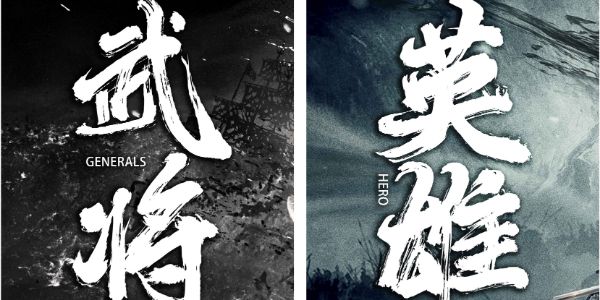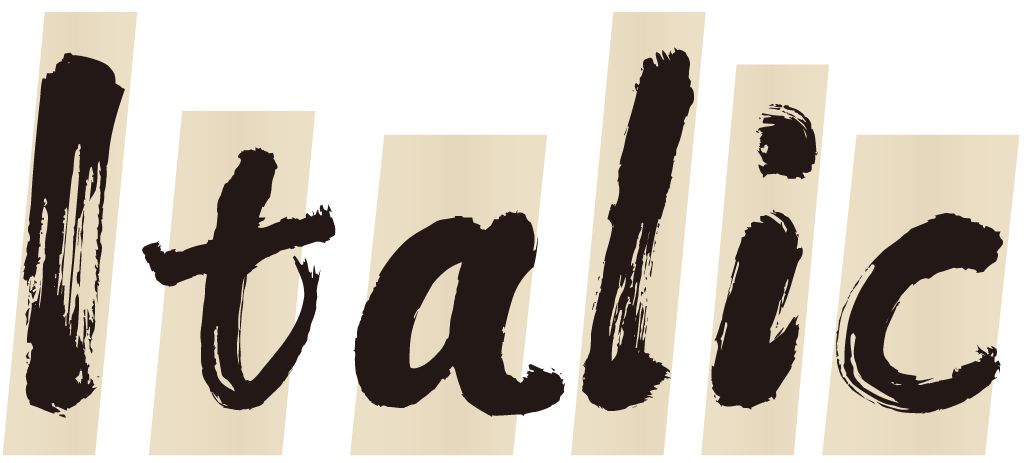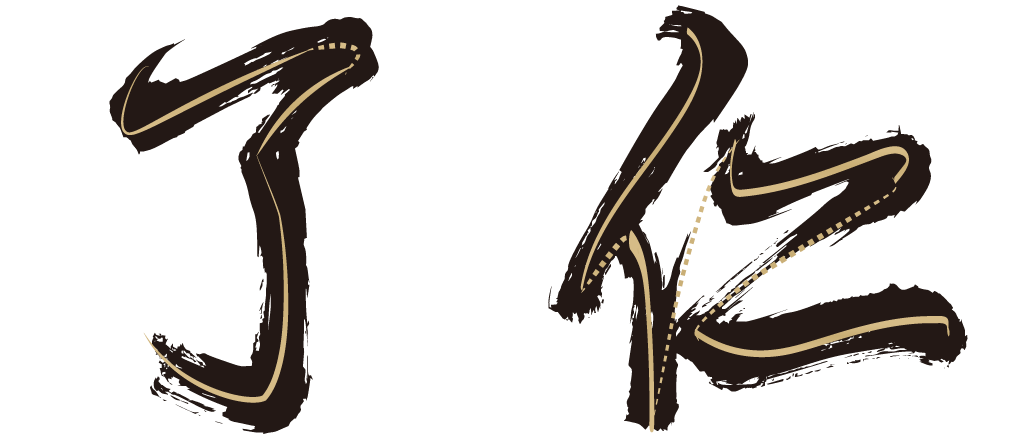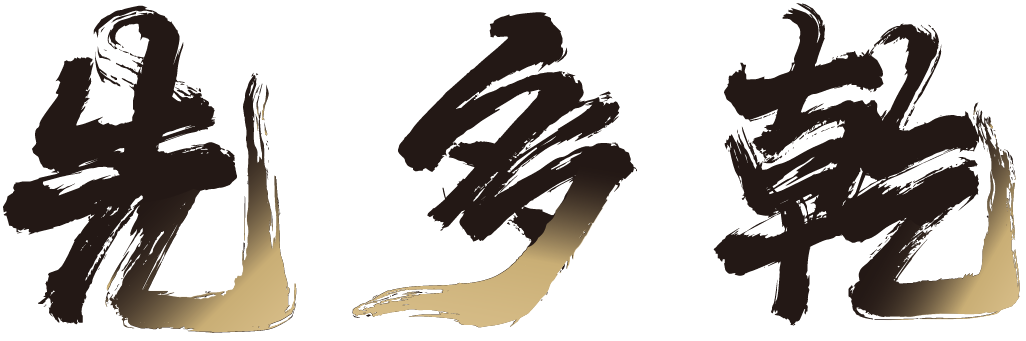
望眼欲穿了大半年,这次它真的来了
还记得柚子发过的《破冰行动》背后隐藏的亮点在这吗?里面提到了青年手写人秦川。
他创作的汉仪秦川飞影,一直在字由上保持着超高使用量。
所以很多人都对他的汉仪秦川漫书,望眼欲穿~
终于,它来了它来了,带着狂放不羁、自由散漫的个性特征,正式上线字由了!
看看它的细节吧,笔画粗壮豪放,撇捺张扬,甩尾有力且有丰富的笔触细节,空间感十足。
断断续续的飞白连笔,让字体好像会呼吸,在虚实和粗细的对比下,更显节奏感和韵律感。
西文字母以意大利斜体为基础,结合部分中文笔画特征,线条流畅,手写感强。
你可以将它广泛应用于多种场景,绝对是当之无愧的主角。